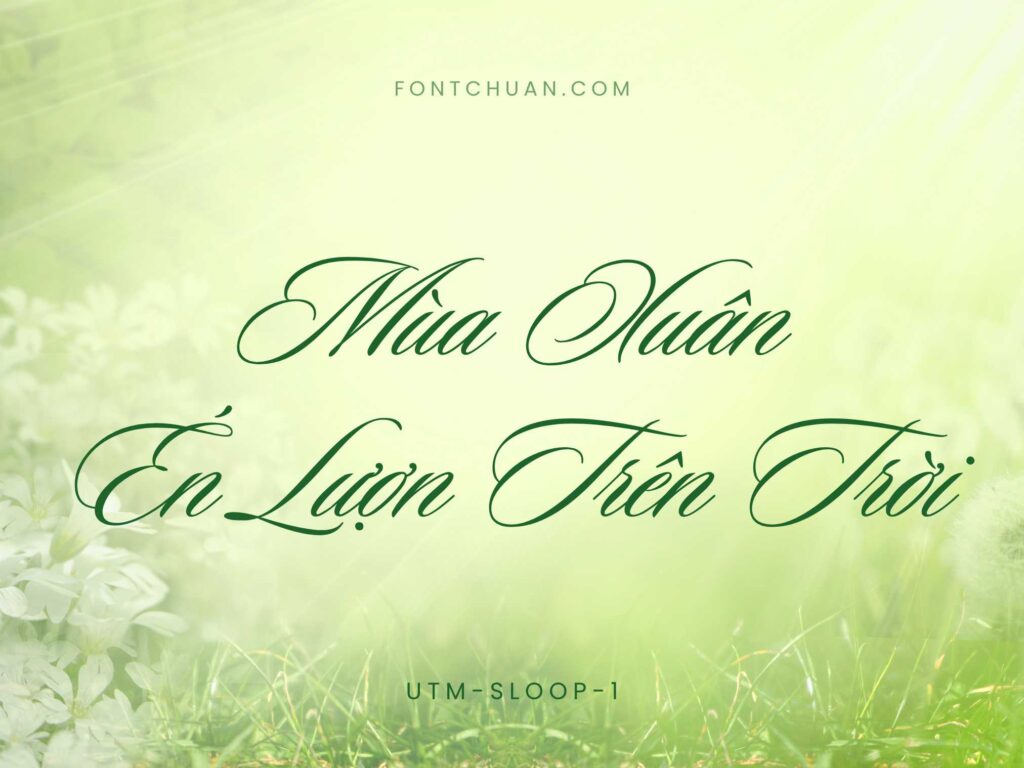
Font UTM Sloop 1 Việt Hóa
UTM Sloop 1 là một font chữ viết tay thanh lịch, thuộc bộ sưu tập font UTM. Với các đường nét mềm mại và uyển chuyển, font này mang lại cảm giác tinh tế và nghệ thuật cho các thiết kế. Đặc điểm nổi bật của UTM Sloop 1 là sự kết hợp giữa phong cách cổ điển và hiện đại, phù hợp cho các dự án như thiệp mời, tiêu đề sách, poster và các ấn phẩm nghệ thuật khác. Font này đã được Việt hóa bởi Thiên Minh, đảm bảo hỗ trợ đầy đủ các dấu và ký tự tiếng Việt, mang lại trải nghiệm sử dụng hoàn chỉnh cho người dùng. Ngoài tiếng Việt, UTM Sloop 1 còn hỗ trợ nhiều ngôn ngữ khác, mở rộng khả năng ứng dụng trong các thiết kế quốc tế. Thành viên của Font Chuẩn đã sưu tầm và giới thiệu UTM Sloop 1 đến cộng đồng thiết kế, giúp họ có thêm lựa chọn cho các dự án sáng tạo.
Với sự kết hợp giữa tính thẩm mỹ và khả năng ứng dụng cao, font này phù hợp cho các thiết kế thiệp cưới, tiêu đề sách, poster và các ấn phẩm nghệ thuật khác.Nhờ các nét chữ mềm mại, liền mạch, UTM Sloop 1 cũng có thể được sử dụng như một Font chữ ký, lý tưởng cho thiết kế logo cá nhân, thiệp cưới hoặc các dự án cần dấu ấn tinh tế và cá nhân hóa.